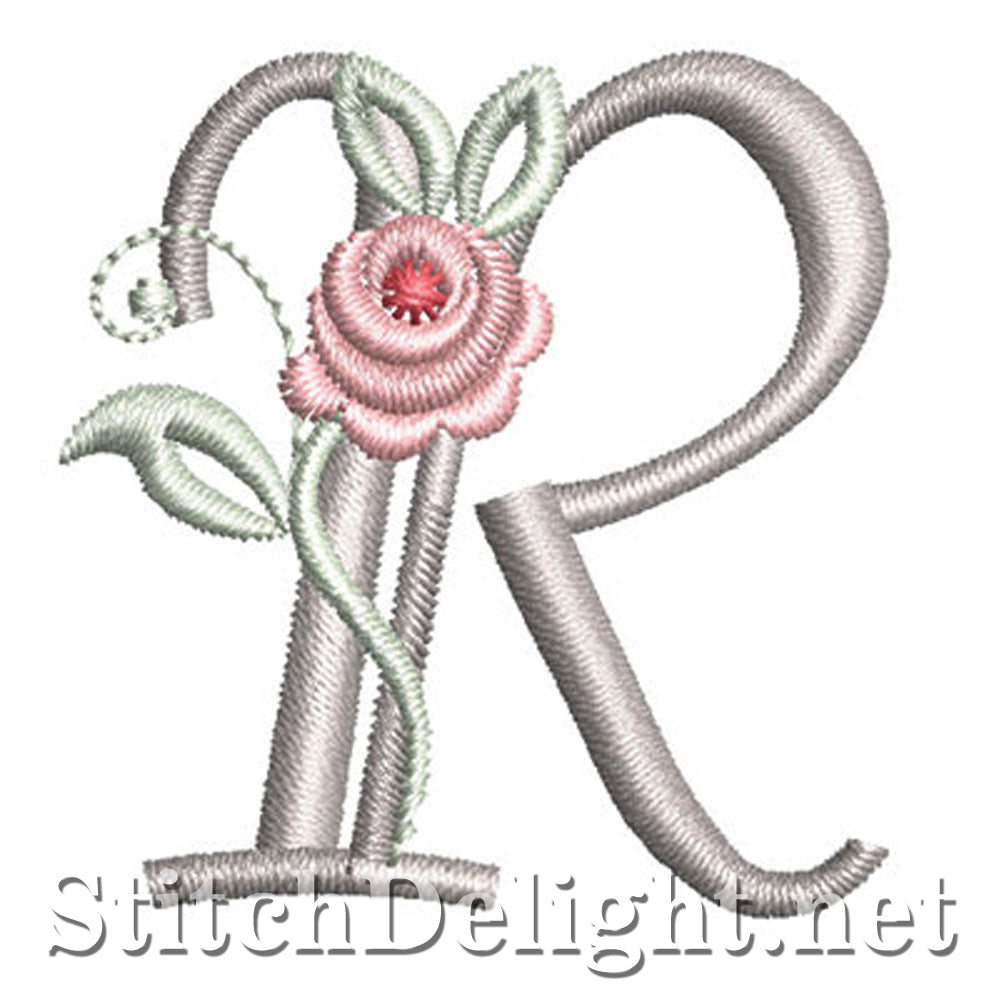
SDS1227 Antique Rose Police R
Personnalisez votre projet avec cet élégant ensemble de monogrammes avec une rose délicate - un superbe ton sur ton cousu. Version BX pour le logiciel Embrilliance - La hauteur des lettres est de 1,20 pouce / 30 mm